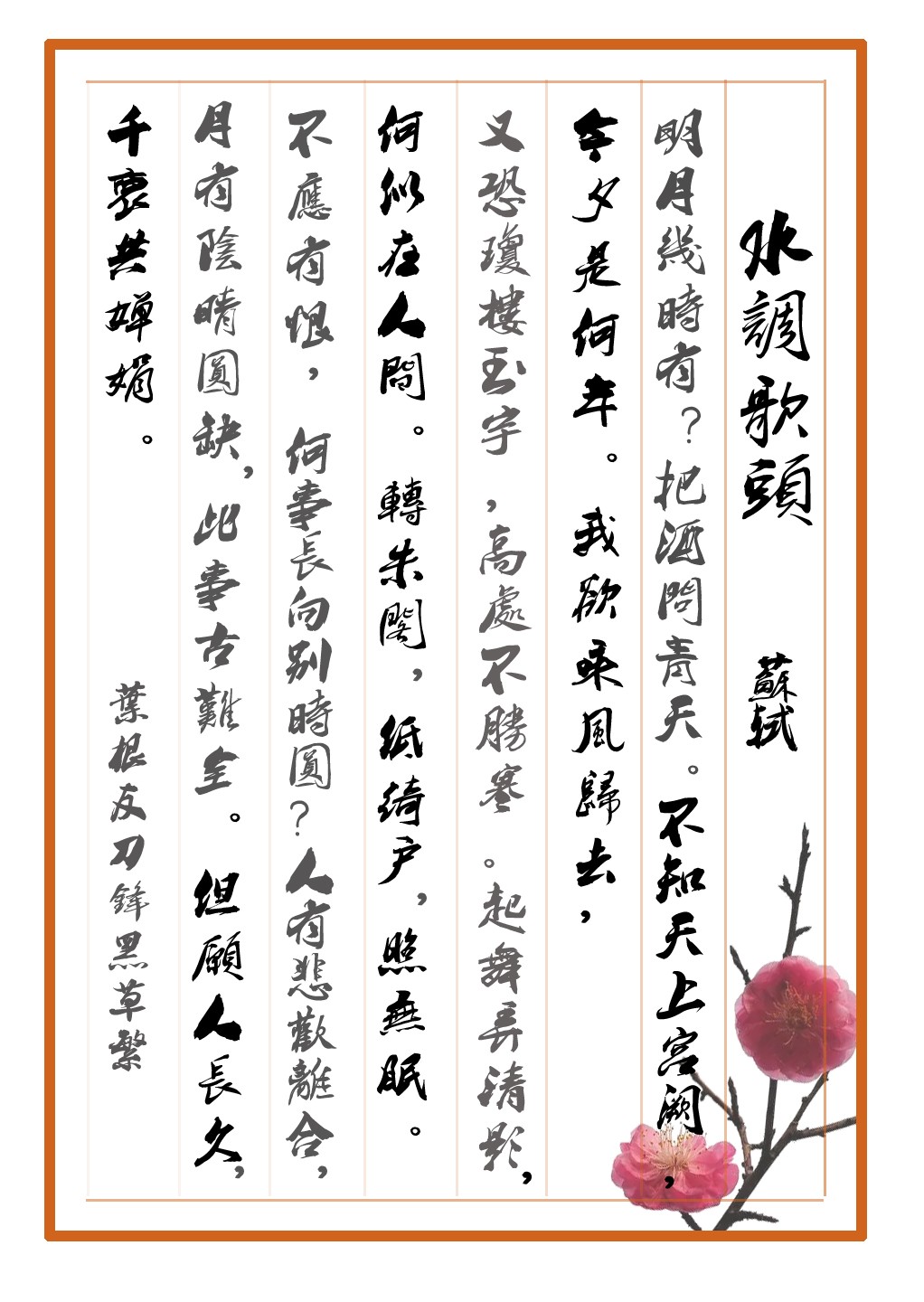
葉根友刀鋒黑草繁
這是一款葉根友字體系列最受歡迎的字體之一。葉根友刀鋒黑草繁體版本是應廣大網(wǎng)友的一致意見,經過三年時間的不斷修正優(yōu)化開發(fā)而成,該字體筆畫風格猶如刀鋒劍影,筆起筆落間一股俠客風的力量縈繞在字里行間,賦予了中國漢字的一種新的犀利,行書與葉氏創(chuàng)新書法的結合,無不演繹出不同的漢字角度。葉根友刀鋒黑草廣泛應用于社會各界的廣告招牌、影視作品以及游戲應用等。葉根友刀鋒黑草繁也是一款刀鋒犀利的筆畫結構,在字體風格上,追求了一種鮮明向上的特點,使整個字型靈動而不失嚴謹,飄逸俊秀,保留了書法原作的原始元素。